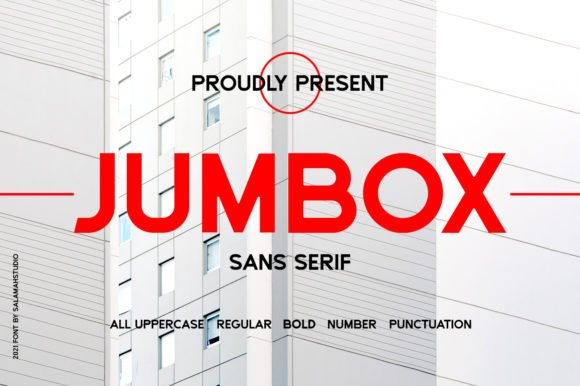
Название: Jumbox Font (2021)
Jumbox - это крутой, смелый и толстый шрифт для печати.
Он будет потрясающе смотреться на любом плакате, листовке или печати.
Используйте этот шрифт для своих проектов и исследуйте его безграничные возможности.